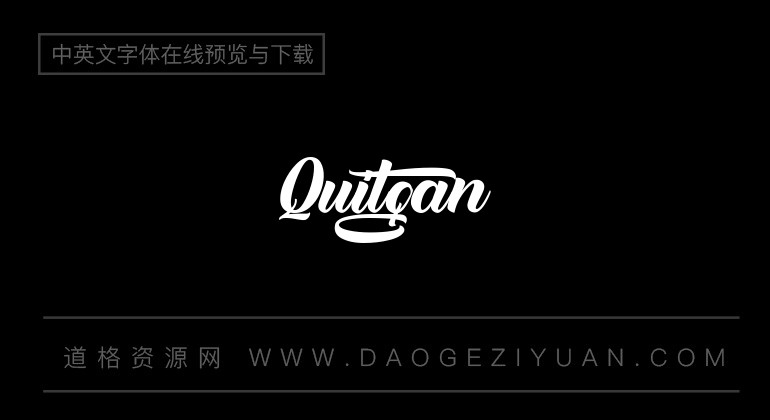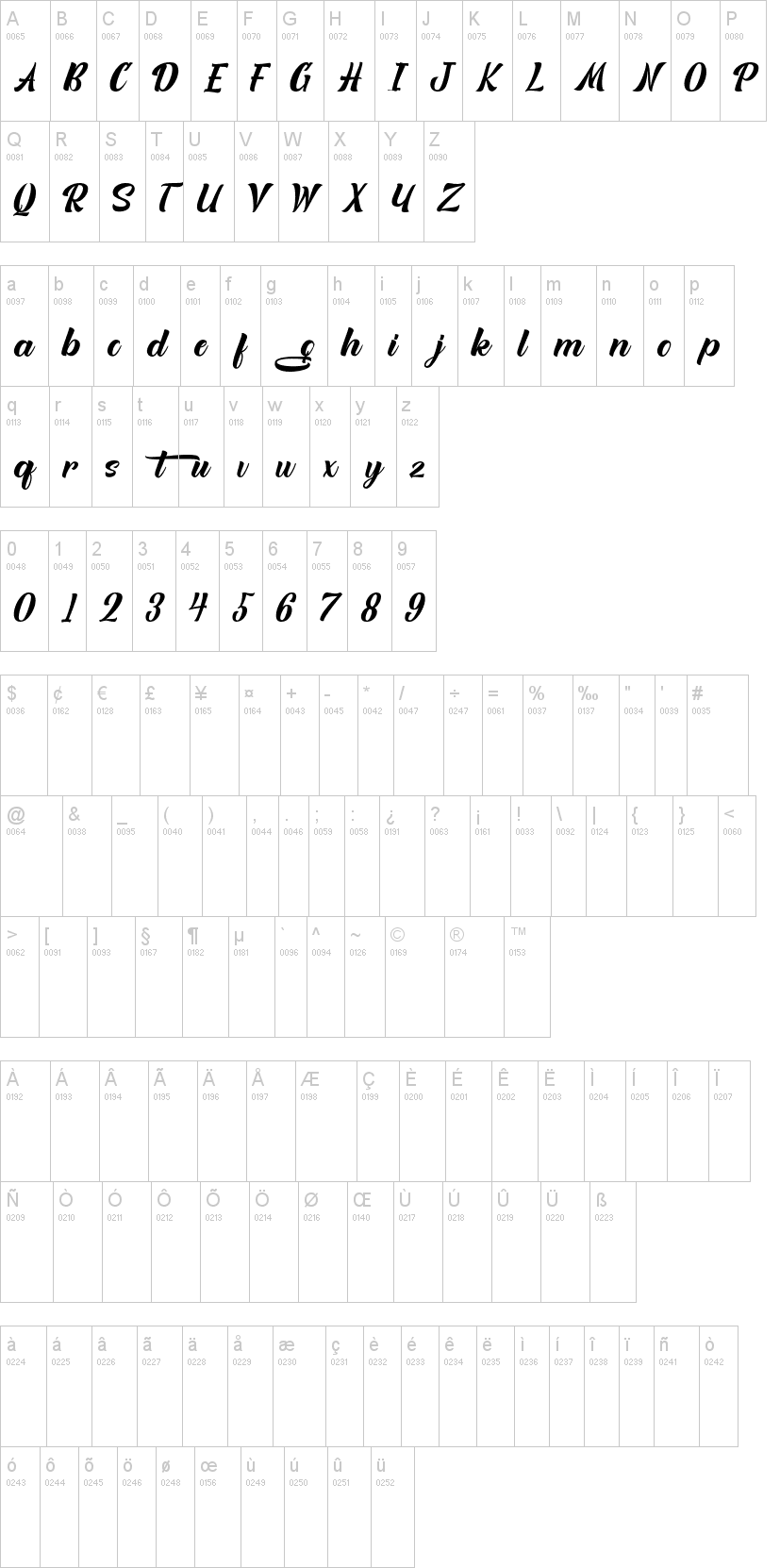
非常抱歉,我不确定您想要了解的是哪种字体。请问您是想了解 Quitgan 字体吗?如果是这样,我会为您提供一些信息。 Quitgan 是一种独特的手写体字体,由一名叫做 Ezeqviel Ergo 设计。这种字体的特点是具有非常明显的手写笔迹,因此给人一种温暖、亲切的感觉。它适用于各种场合,例如包装设计、广告、海报等等。 Quitgan 字体包括多种风格和变体,包括粗体、斜体、下划线等等。这种字体可以免费下载并在个人和商业项目中使用。如果您正在寻找一种独特、温馨的字体,那么 Quitgan 字体可能是一个不错的选择。内容介绍
Quitgan是一款非常不错的手写艺术字体,具有很好的视觉感,适合于文化类的宣传设计、商业类品牌的广告和产品包装设计以及个性化文字排版等较多场景。